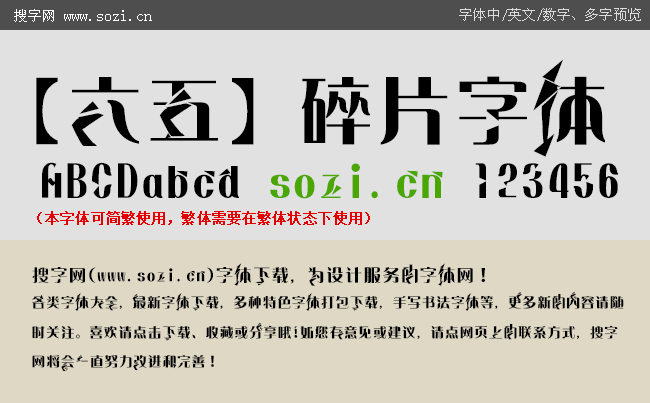
碎片字體
搜字網(wǎng)給大家提供一款碎片字體手機(jī)中文字體下載。這款手機(jī)字體是以倩體字體為原形的一款藝術(shù)設(shè)計字體,個別字體筆畫及部首進(jìn)行了碎片式的藝術(shù)變形。是一款很有趣的卡通藝術(shù)字體,特別適合喜歡手機(jī)字體個性一些的朋友在手機(jī)上安裝使用。